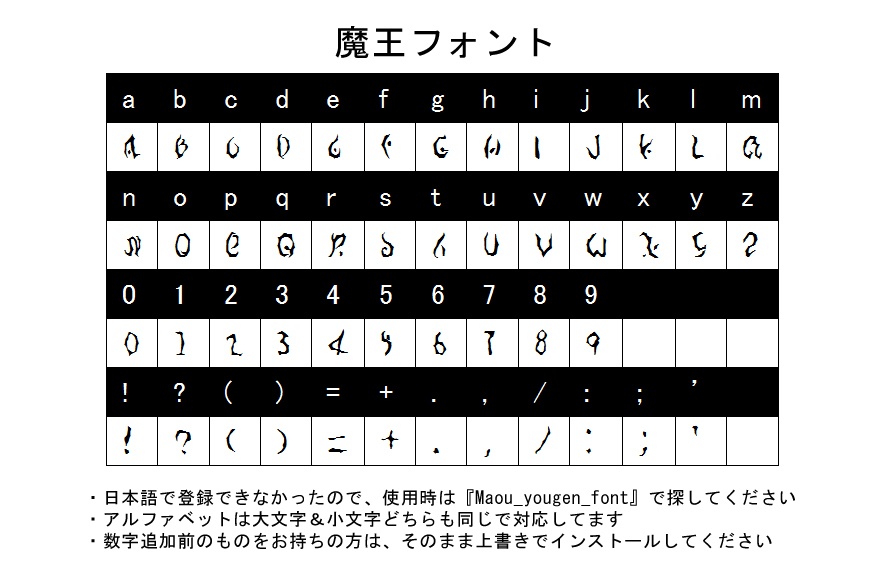
【素材】魔王フォント(改)【無料&投げ銭】
魔法陣グッズが欲しくて魔法陣作りを始めましたが、『オリジナル漫画もあるし、どうせならフォントから作ろう』という安易な考えで作成しました。 読めそうで読めなさそうでその気になれば読める奴です。 どなたさまもお好きなようにご利用ください。 『ファンタジー…、好きに設定できるのはいいけど、逆に設定するべきものが多すぎてフォントまで手が回せない…っ!』と行き詰ってる方は、ぜひとも諦めてこのフォントを使用し、そのぶん楽しく物語を書き進めていただきたいです。心の底から応援してます。 エアブーに間に合わせようと思ったら数字まで手が届かなかったので、後日しれっと追加されてると思います。『数字も寄越せよぉぉぉ!』と机を打った頃にまた見に来て下さい。 *2021.5.3:数字&その他を追加しました。アルファベットは大文字小文字両方に対応しました。 *『無料素材は投げ銭も作った方がいいよ!』とアドバイスされたので追加してみました。お気に召した方に心づけをいただけたら幸いです。中身はすべて同じです。 *こちらはダウンロード商品につき、BOOTHの規約でキャンセル不可となっています。万一を考え。お遊び気分で高額なものをカートに入れたりしないようお気を付けください。もちろん、富豪の方からのお気持ちはありがたく頂戴いたします。